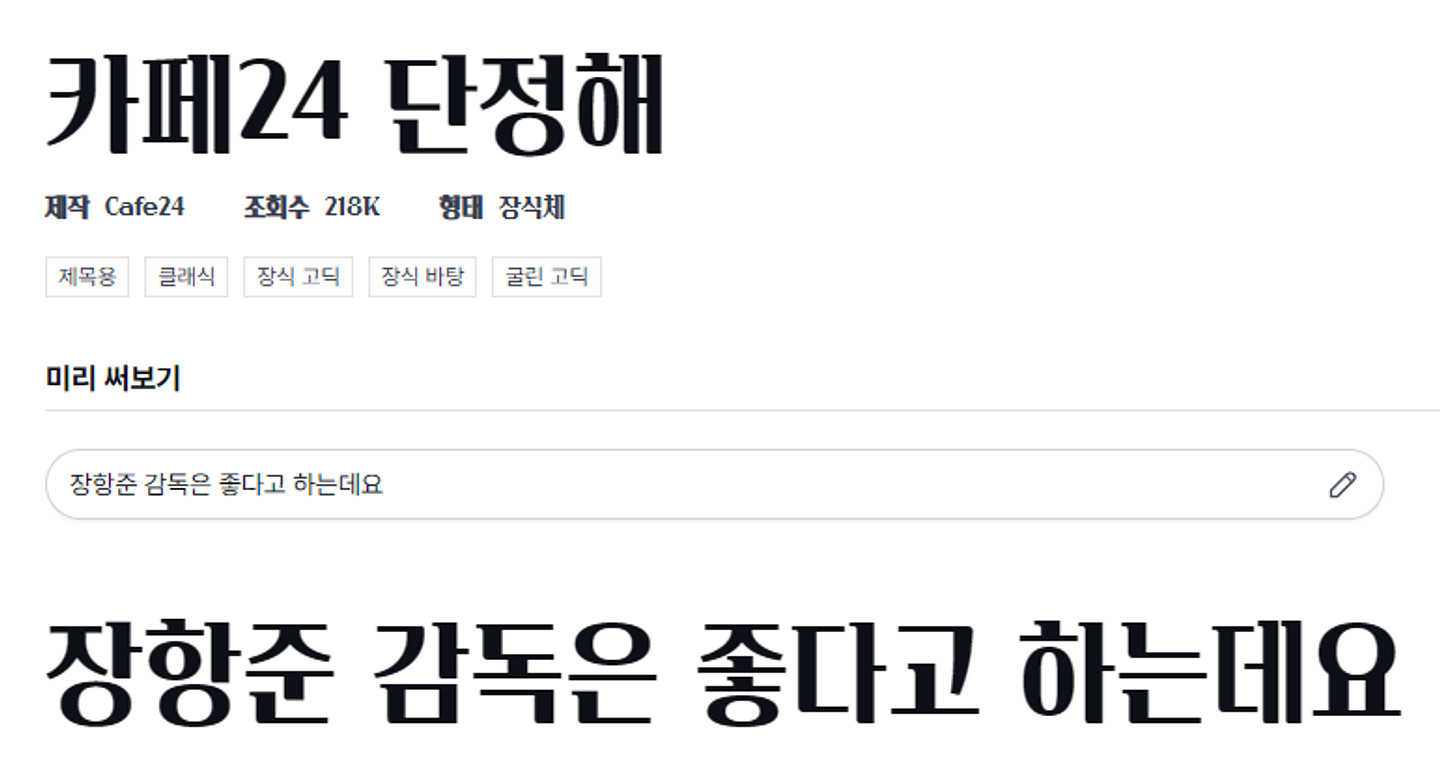
도톰하고 글씨 예쁜데요. 이 폰트 뭘까요? 아래 링크에서 봤습니다. 알려주시는 분 복받으실 거예요. 어린 양에게 자비를 베풀어주세요. https://youtube.com/shorts/07WBvh8e9Xg?si=CQoBsQLXChDySbtV
Cafe24 丹青海 Cafe24